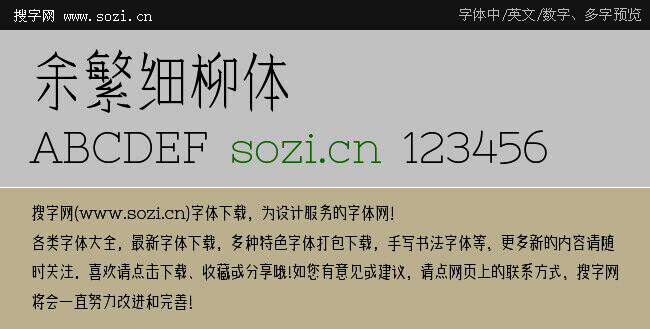
余繁細柳體
搜字網(wǎng)提供一款余繁細柳體中文藝術(shù)字體下載,余繁細柳體是 一款筆畫模仿仿宋的大字面細字體。在字高32px時,筆畫寬度約為1px。所以這款字體不適合32px以下的字號。字體開源可以免費商用。適合圖書設(shè)計、包裝設(shè)計、海報設(shè)計等應(yīng)用。